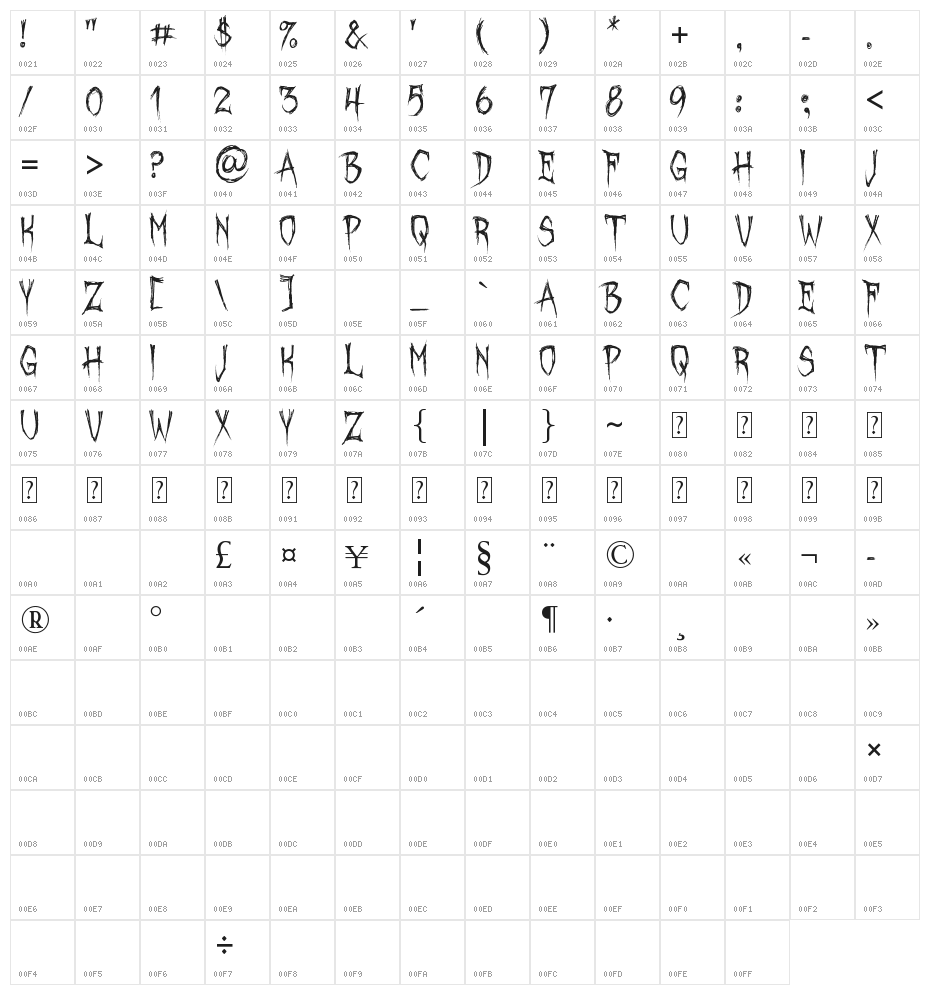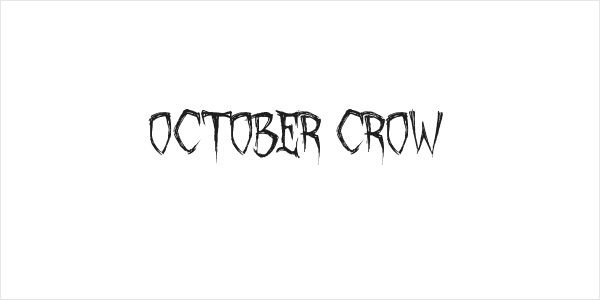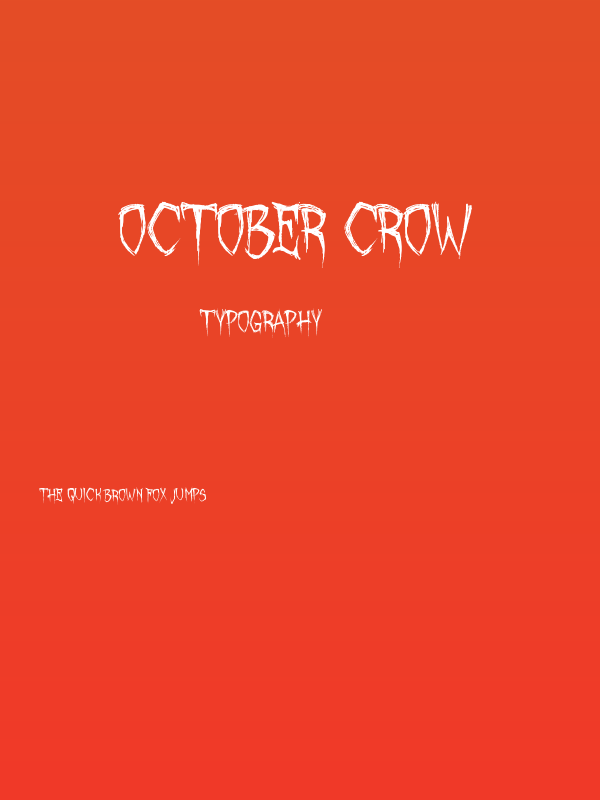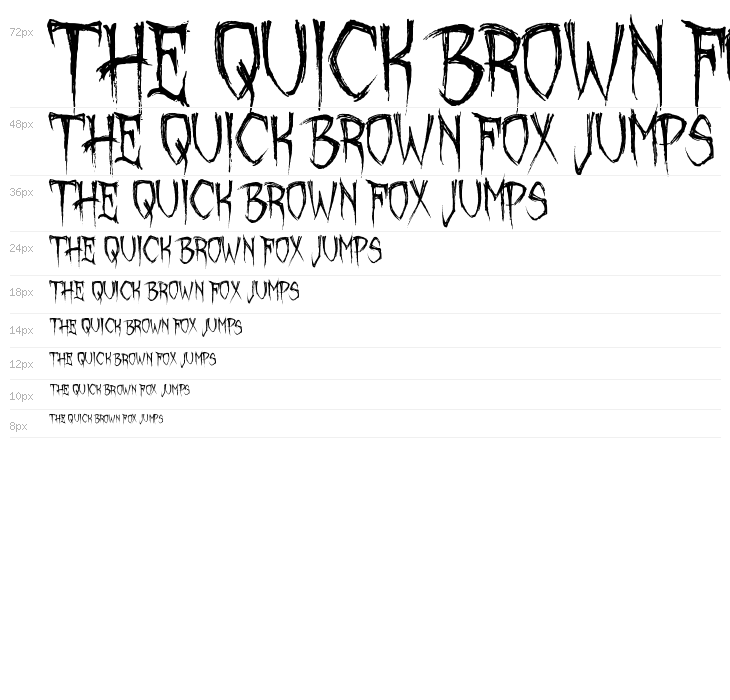
October Crow Font
| कंट्रास्ट | High |
| समग्र शैली | Gothic, Dramatic, Edgy |
| उपयोग का मामला | Headlines, Posters, Themed Events |
| सुझाए गए प्रोजेक्ट | Ideal for horror-themed designs, Halloween promotions, and edgy graphic projects. |